Как связать буквы в рабочие группы: план зависимостей для рукописного шрифта
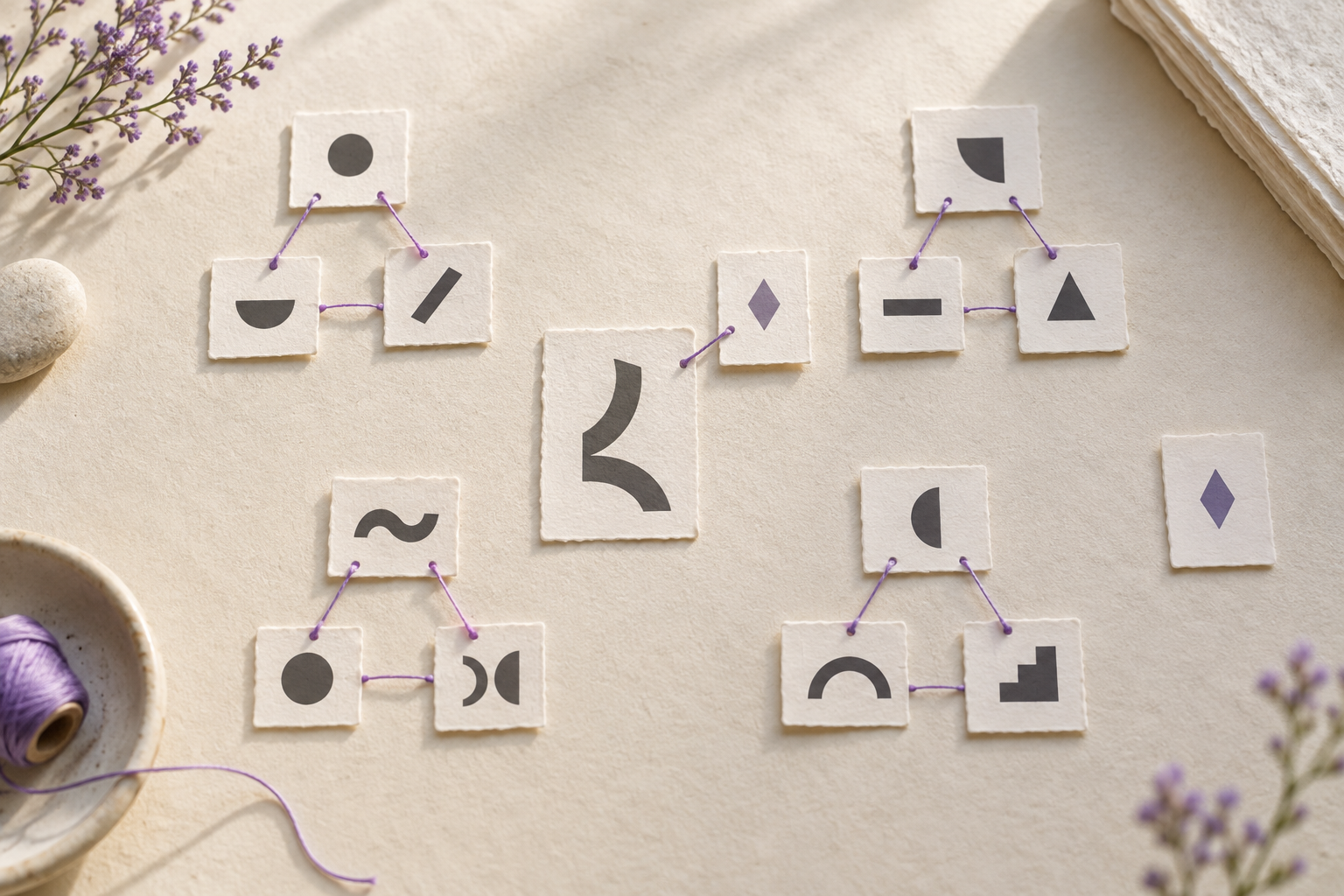
Список символов отвечает на вопрос, что должно войти в шрифт, но не подсказывает, в каком порядке это рисовать. Если идти подряд от А до Я, зависимые формы легко приходится переделывать, а важные проверки вспоминаются в конце. План зависимостей связывает знаки по общим конструктивным решениям и превращает набор в последовательность небольших задач с понятным результатом.
Сначала зафиксируйте состав, затем стройте порядок
Этот план нужен после того, как вы уже определили назначение шрифта и составили перечень нужных букв, цифр и знаков. Он не заменяет решение о том, какие символы включать. Его задача — организовать выполнение выбранного объёма: что можно делать параллельно, что опирается на более раннее решение и в какой момент проверять группу целиком.
Возьмите свой утверждённый список и присвойте каждому знаку временный статус: «самостоятельный», «имеет родственные формы», «зависит от другой формы» или «требует отдельной проверки». Эти метки не оценивают сложность буквы навсегда. Они помогают заметить связи, из-за которых порядок «по алфавиту» оказывается неудобным.
Что считать зависимостью между знаками
Зависимость возникает, когда решение по одному знаку меняет критерии или объём работы над другим. Это может быть общая конструктивная основа, повторяющийся штрих, надстрочный элемент, общий размер, соединительный выход или проверка в одном текстовом контексте. Сходство внешнего вида само по себе ещё не означает, что один глиф нужно копировать в другой.
Например, если в проекте предусмотрены «е» и «ё», базовую форму «е» разумно согласовать раньше, чем добавлять точки над «ё»: иначе при изменении ширины или верхней зоны придётся заново размещать диакритику. Пара «и» и «й» тоже подсказывает простую связь: сначала проверьте корпус буквы, затем отдельно спроектируйте кратку и оцените итоговый силуэт. Это не значит, что кратка всегда должна быть механически добавлена к неизменной букве: важны пропорции, расстояние и визуальный баланс.
Другой тип связи — семейство конструкций. В конкретном почерке несколько знаков могут использовать похожую дугу, петлю или способ входа в соединение. Запишите, какие именно решения общие, а какие надо сравнить отдельно. Близкое происхождение штриха не гарантирует одинаковой ширины, наклона или поведения в слове.
Есть и контекстные зависимости. Форма отдельной буквы может выглядеть удачно на листе, но теряться рядом с соседями, с которыми часто встречается. Поэтому группа работ считается законченной не тогда, когда готовы отдельные рисунки, а когда вы просмотрели их в нескольких коротких сочетаниях и проверили переходы между штрихами.
Постройте карту групп, а не длинную очередь
Для начала соберите карточки символов и разложите их на небольшие группы по одному основанию. У каждой группы должна быть проверяемая цель. Если в одну карточку попали «все строчные», «всё редкое» и «все сложные», это уже не задача, а контейнер для разных задач.
В простом реестре достаточно таких полей:
- знак или конкретная группа знаков;
- связь с уже готовым решением;
- что именно нужно нарисовать или уточнить;
- как проверить результат;
- статус и следующий шаг.
Пример формулировки для «ё»: «Проверить точки над утверждённой формой “е”; сравнить высоту, расстояние и ширину всей буквы; проверить в словах “ёлка”, “берёза” и “чёрный”». Это полезнее, чем запись «сделать ё»: действие и критерий результата понятны, а неудачную часть можно исправить отдельно.
Полезно разделить связи на три типа. «Сначала» означает, что без одной формы вторую нельзя закончить: например, нужно утвердить базовую конструкцию прежде, чем настроить добавленный к ней элемент. «Вместе» означает, что знаки удобно сравнить на одном этапе, хотя они не копируют друг друга. «Проверить после» отмечает контрольную точку: буквы рисуются независимо, но их общий ритм нужно оценить после сборки группы.
Выберите опорные решения
Не все карточки имеют одинаковую ценность для дальнейшей работы. Опорной становится форма, от которой зависят другие решения: например, общий наклон, высота строчных, характер соединения или то, насколько компактным будет корпус. Выбирайте опору по своему шрифту, а не по универсальному списку «главных букв».
Практический способ — сначала нарисовать несколько контрастных представителей выбранного набора, которые выявляют разные конструктивные вопросы. Одни покажут, как устроены вертикали и дуги, другие — диагонали, петли или выходы. После этого зафиксируйте правила, которые действительно повторяются. Не распространяйте частное решение на весь алфавит лишь потому, что оно хорошо сработало в одной букве.
Опорные карточки должны иметь короткий итог: что уже решено и что пока остаётся открытым. Например: «Наклон выбран; соединительный выход проверен в двух словах; ширину соседних букв ещё сравнить после набора группы». Такая запись помогает не принимать временную находку за законченное правило.
Когда обновлять карту зависимостей?
После проверки каждой небольшой группы и всякий раз, когда меняется опорное решение. Не нужно переписывать весь план ежедневно, но статусы и блокировки должны соответствовать тому, что происходит сейчас.
После фиксации состава знаков свяжите только те задачи, которые действительно зависят друг от друга. Рисуйте небольшими группами, определяйте результат до начала работы и проверяйте его в словах. Тогда пересмотр одной формы затронет понятный участок плана, а независимые части набора смогут двигаться дальше.